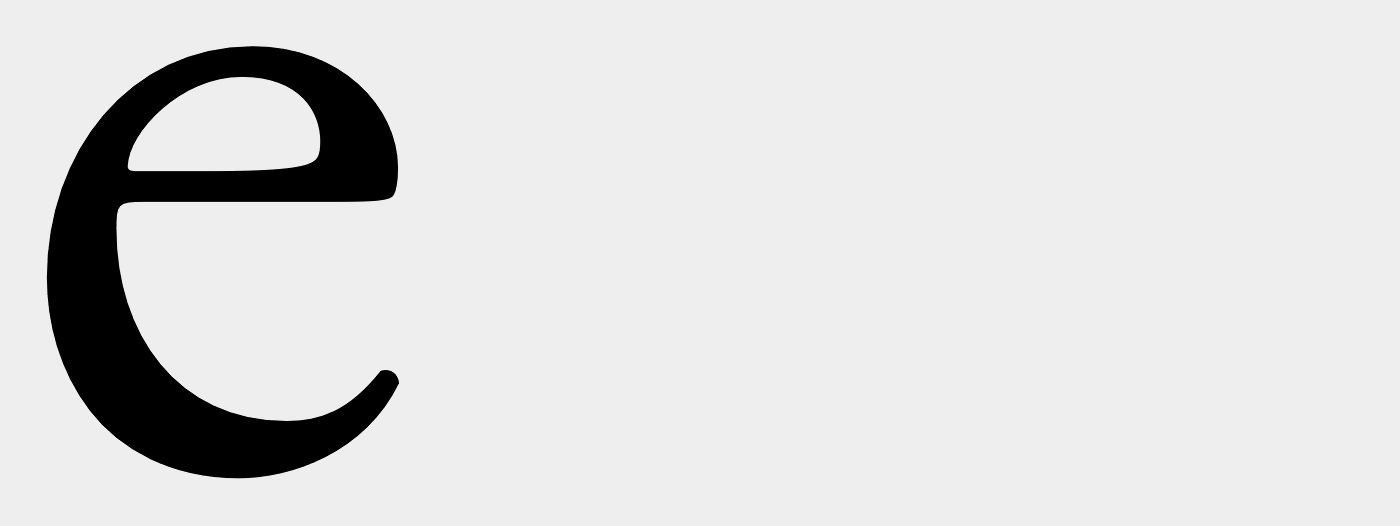
Frische Alternativen zur Bembo gesucht
fallen Euch spontan frische, unverbrauchte Alternativen zur Bembo ein? Für Tipps wäre ich von Herzen dankbar!
Nachtrag: Und gleich noch eine Frage hinterher: Wenn Ihr eine Didot kaufen müsstet, welche Variante würdet Ihr wählen?
Ich kann nur meinen Post von hier wiederholen und hoffen, dass er hier hilfreicher ist: :-)
Die Cardo. Ist zwar eher nicht frisch, dafür aber vermutlich unverbraucht. Und sie wartet mit einem großen Arsenal mediävistischer Spezialglyphen auf. Und das R hat schon in der Standardversion einen kürzeren Schweif. Ich hab neulich erst festgestellt, dass die Bembo ja ein Alternativ-R mit kürzerem Schweif drinhätte, aber ich habe es in allen Büchern, in denen sie so gern benutzt wird, nie gesehen. Reißt m.E. immer gewaltige Löcher in den Text.
Nicht ganz so frisch aber teilweise sehr gut ausgebaut, mit optischen Größen und evtl. durch Adobe CS oder Mac OS X schon ein paar Appetithäppchen auf Deinem Rechner:
Etwas spritziger:
Und wenn Du ganz mutig sein willst:
Edit wollte auch noch etwas loswerden:
Im Typographie-Wiki steht, dass die Andron eine venezianische Antiqua ist, die Bembo soll hingegen französisch laut Wikipedia sein (im Widerspruch zu unserem Wiki). Meine üblichen Unterscheidungsmerkmale (W* und e) sagen mir, dass beide venezianische Antiqua seien. Mag mir bitte jemand helfen? Ich steh grad voll auf dem Schlauch.
* Sieht das W aus, als ob sich zwei V überlappen, ist es eine französiche Renaissance-Antiqua. Ist der Strich im Inneren des e waagerecht, ist es ebenso französisch.
Hat schon mal einer von Euch etwas von der DietDidot von Paratype gehört? Ich bearbeite gerade ein Projekt, bei dem ich diese Schrift benötige. Jetzt ist die Frage, ob ich nur die notwendigen zwei Schnitte oder gleich ein ordentliches Päckchen kaufe. Ich habe noch keine OTF-Didot, deswegen wäre eine Anschaffung in dieser Richtung für mich auch unabhängig vom konkreten Projekt nicht verkehrt. Die Frage ist nur, ob es sinnvollerweise diese in mehreren Schnitten sein sollte oder lieber nur zwei Schnitte DietDidot und dafür noch eine andere on top.
Hat zufällig schon mal einer von Euch mit diesem Schätzchen gearbeitet?
Die didoteske Yo-Familie von James Montalbano gibt es bei Terminal Design:
Over the years, I’ve been asked to draw a lot of Didot-like designs. It seemed that every magazine art director absolutely had to have their own version of the design.
Remembering Photo-Lettering’s wonderful “One Line Manual of Style”, which showed page after page of Didot and Bodoni types, all drawn by the great NYC lettering artists of the 50s and 60s, I decide that I would create my own large collection of Didones.
The Yo family was originally planned to have 26 widths each with 20 weights, 520 different fonts. Sanity forced me to scale my ambitions back to a 100 font family. I gave them all names to keep them straight in my head. A name beginning with the letter A would be the narrowest and Z the widest. So you have Yo Andy and Yo Zelda at the extremes. Yo Lucy in the middle, and Yo Frankie and Yo Sophie where you would expect them to be.
I mistakenly thought that a 100 font super-family of Didot-like fonts would be enough. I was wrong. No sooner than they were released I was inundated with requests for their italic counterparts. The italics have been added and now that 100 font super-family is now a 200 font really big super-family!
Als Bembo-Alternative werfe ich mal noch folgendes in die Runde:
• Agmena von Jovica Veljović (Linotype)
• Albertina von Chris Brand (Dutch Type Library | Monotype)
• Birka von Frank Luin (Omnibus Typografi)
• Columbus von David Saunders (Monotype)
• Dante von Giovanni Mardersteig, Ron Carpenter (Monotype)
• Fabiol von Robert Strauch, Oliver Linke (Lazydogs)
• Griffo Classico von Francesco Griffo, Frank Luin
• Legacy Serif von Nicolas Jenson, Arnholm Ronald (ITC)
• Maiola von Veronika Burian (Typetogether)
• Rialto von Giovanni de Faccio, Lui Karner (df Type)
(Ein Schriftmuster der Rialto müsste dir Sebastian liefern können.)